Arabisch
Die arabische Schrift verbindet eine ganze Weltregion: vom Atlantik bis zum Indischen Ozean wird sie für Sprachen so unterschiedlich wie Arabisch, Persisch, Urdu oder Paschtu verwendet — geschrieben von rechts nach links, in fließenden Bögen.
Aus dem nabatäischen Alphabet hervorgegangen, verbreitete sich die arabische Schrift mit dem Islam ab dem 7. Jahrhundert über große Teile Asiens und Afrikas. Sie kennt 28 Buchstaben, die ihre Form je nach Stellung im Wort verändern, und macht ein Lautbild aus Bögen, Punkten und Linien.
Frühe Stile wie Kufi sind streng geometrisch, spätere Stile wie Naschi, Thuluth oder Diwani lassen die Linie tanzen. So wurde die arabische Schrift nicht nur Verkehrsmittel des Gebets und des Handels, sondern zur Königsdisziplin der Kalligrafie.
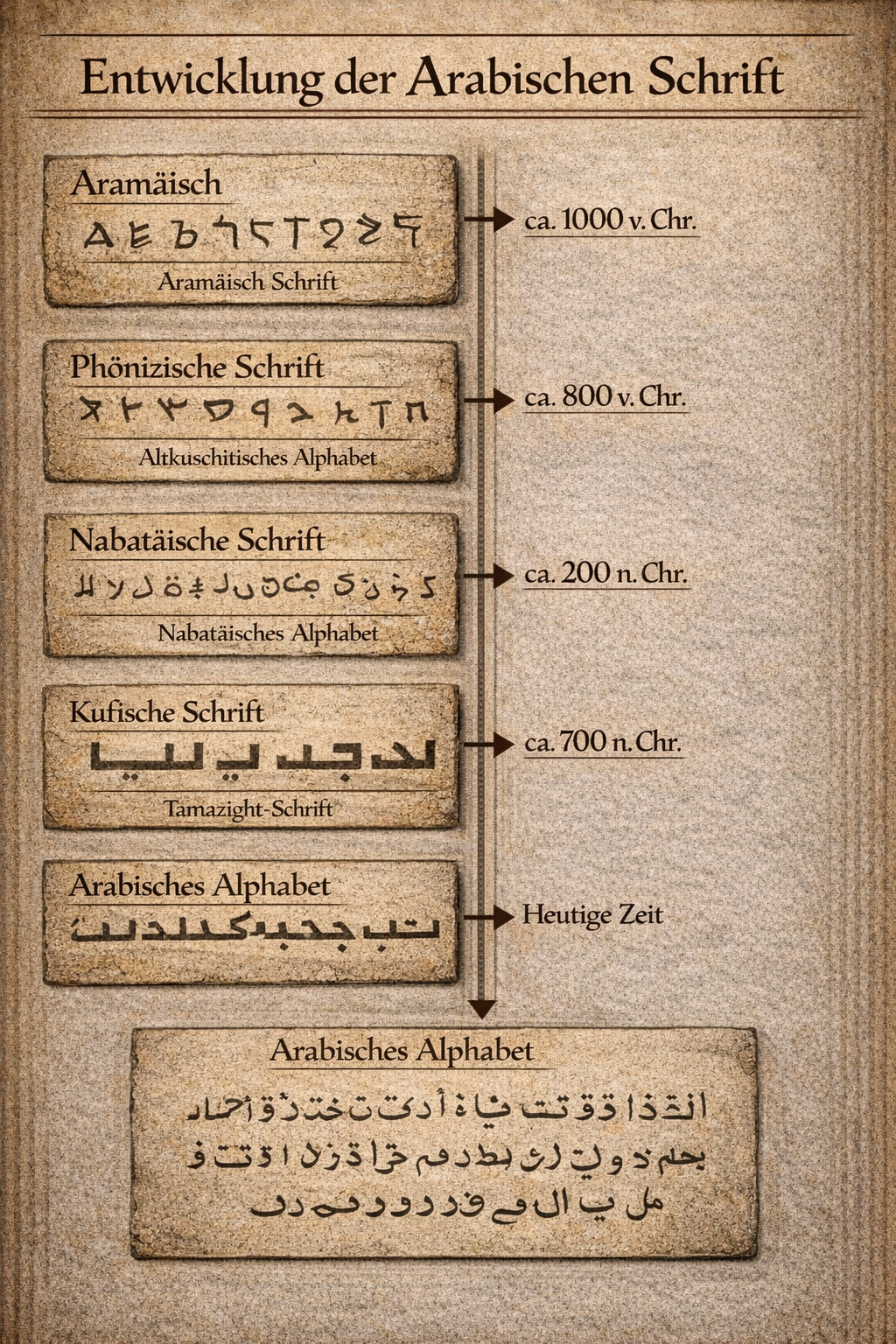
Ab dem 7. Jahrhundert
Eine Schrift, viele Sprachen
Arabische Schrift
Das Alphabet
28 Buchstaben in vier Formen
Jeder Buchstabe kennt eine Form für Wortanfang, Mitte, Ende und Alleinstellung. Dadurch fließt die arabische Schrift wie eine Linie, die nur an wenigen Stellen abreißt — Kalligraphie und Lesefluss sind hier von Anfang an eins.